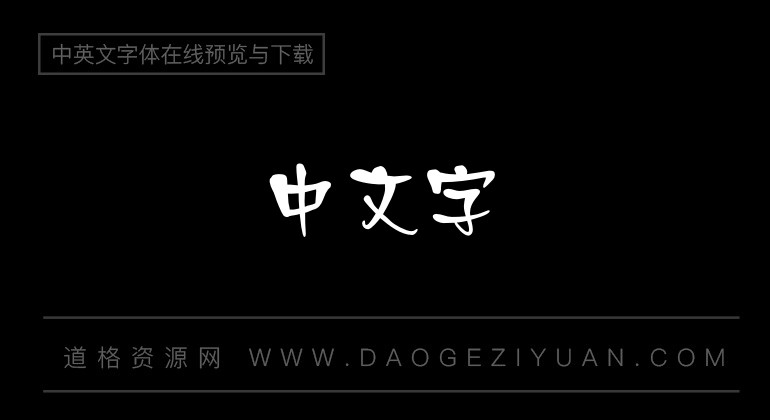
蒙纳简广告
蒙纳简广告字体是一种经典的、优雅的字体,它的特点是简洁、精致、明快。它的设计原则是:简洁明快,有力量,容易让人理解。它的字体结构完整,符号体现出节奏感,字符结构清晰,比例协调,表现出视觉上的优势。通常情况下,它适用于广告、标识、海报、杂志封面等场合。
蒙纳简广告是一款非常不错的手写艺术字体,具有很好的视觉感,适合于文化类的宣传设计、商业类品牌的广告和产品包装设计以及个性化文字排版等较多场景。